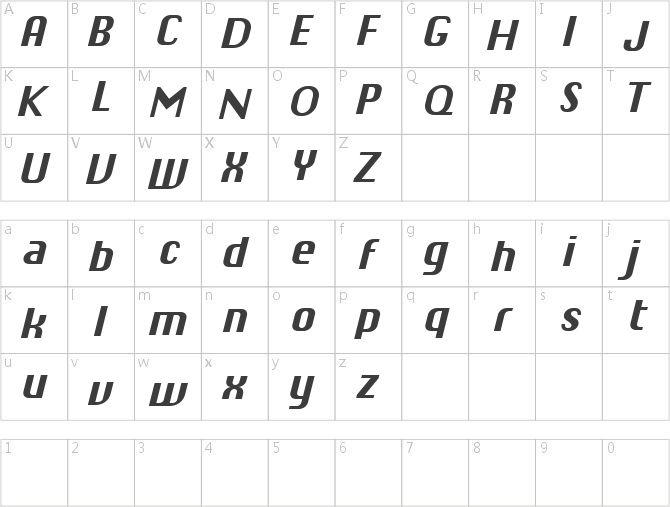
Chiq_Reduced_BoldItalic 詳情頁
Chiq_Reduced_BoldItalic
Chiq_Reduced_BoldItalic字體字庫是一款讓人賞心悅目、百看不厭的英文字體,適合各類廣告和產品包裝設計應用,字體大小0.02MB,格式為ttf字體,上傳用戶是文生電腦,作者/版權方為未知